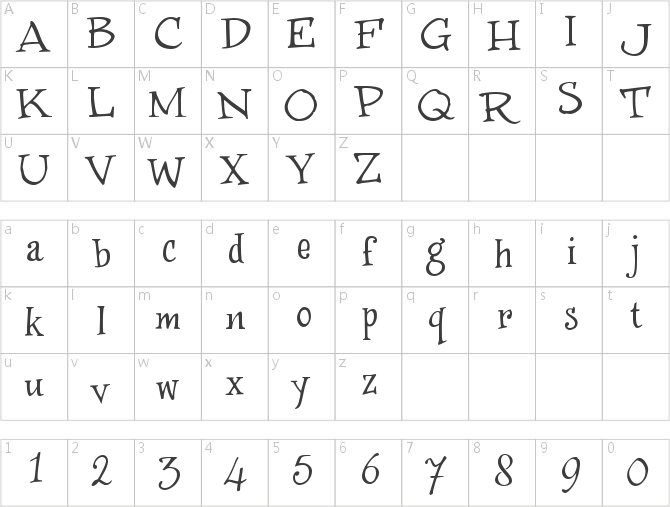
字体名称: Winston
WinstonNero_Trial
WinstonNero_Trial介绍
WinstonNero_Trial字体字库是一款让人赏心悦目、百看不厌的英文字体,适合各类广告和产品包装设计应用,字体大小0.03MB,格式为ttf字体,上传用户是顺新广告?,作者/版权方为未知